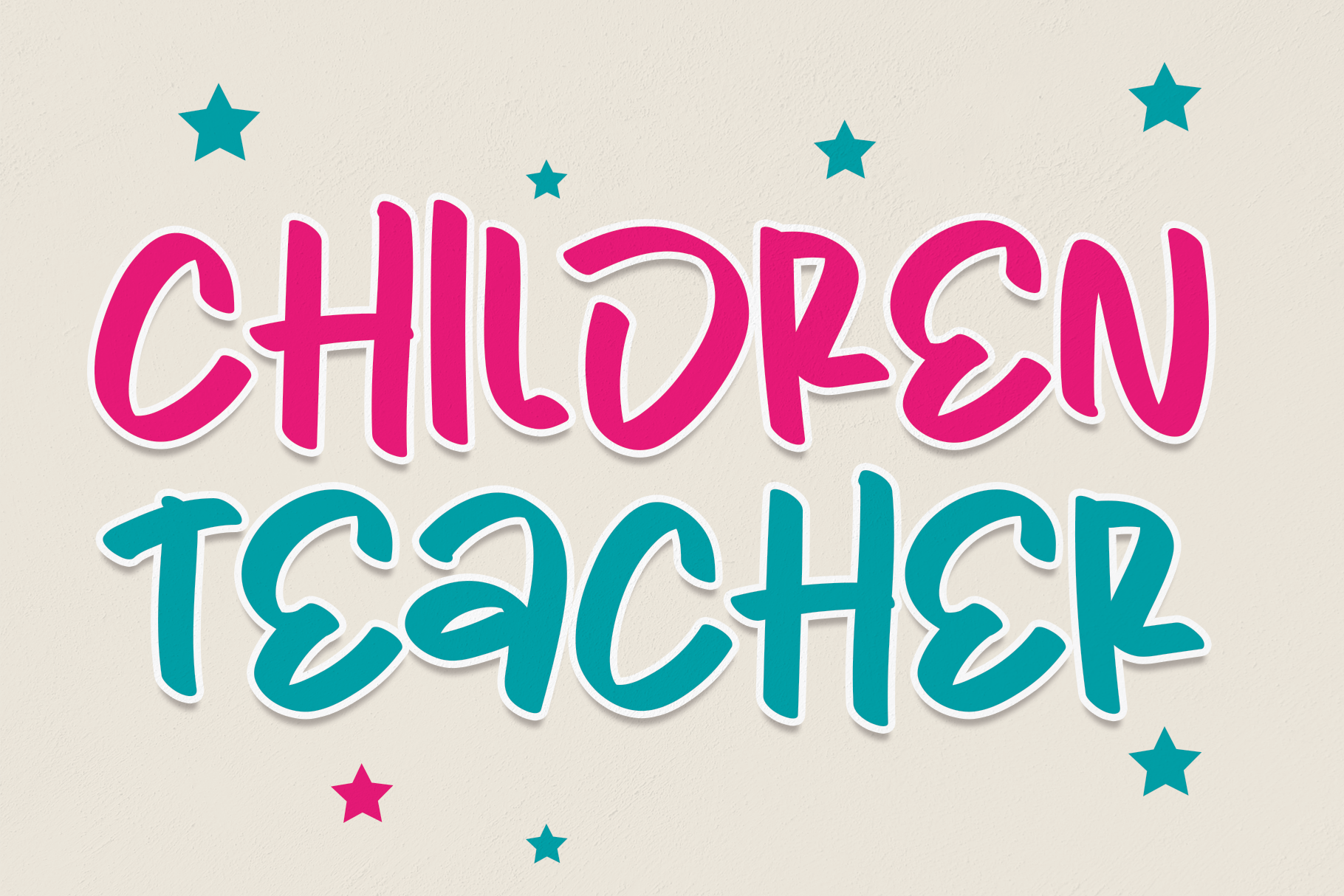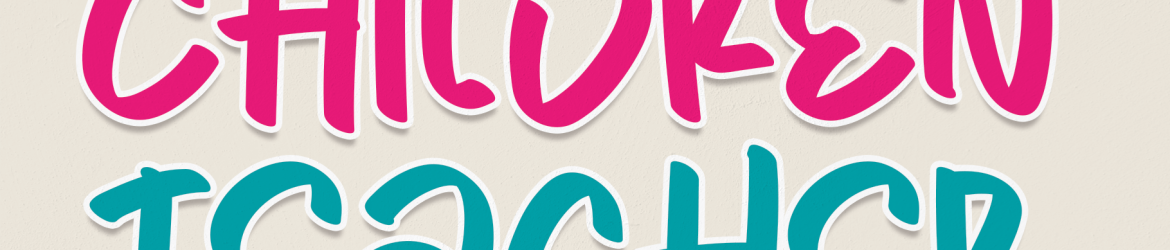
Children Teacher Font – Download Grátis
Esta fonte ‘Children Teacher Font’ é uma opção simples e descontraída para projetos digitais que valorizam a informalidade e o conforto. Perfeita para adicionar um toque leve e amigável aos seus trabalhos de design, essa fonte será facilmente adaptada às diversas ideias criativas. Ideal para criações infantis ou até mesmo para texturas humanizadas em sites educacionais, a Children Teacher Font é uma escolha versátil que vai encantar tanto os designers quanto os amantes do design gráfico. Seu charme casual e seu estilo relaxado permitem que você personalize cada projeto de maneira única, criando um toque pessoal e alegre para seus designs. Seja para adicionar um pouco mais de vida aos textos dos alunos ou até mesmo para dar uma pitada de familiaridade em suas páginas educacionais, essa fonte é perfeita tanto para os designers quanto para quem quer transmitir conteúdo de forma amigável e descontraída.